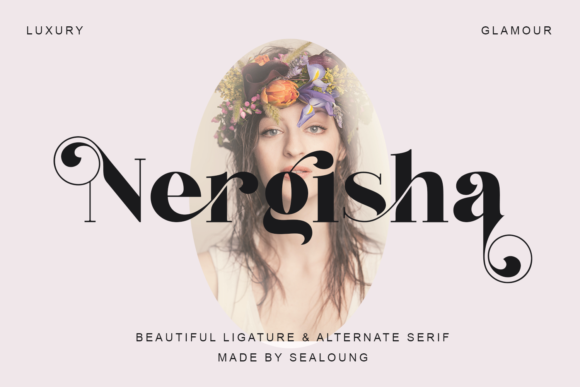
Nergisha - это элегантный и модный шрифт с засечками.
Он отличается уникальной формой символов и, несомненно, возвысит каждое из ваших любимых творений.